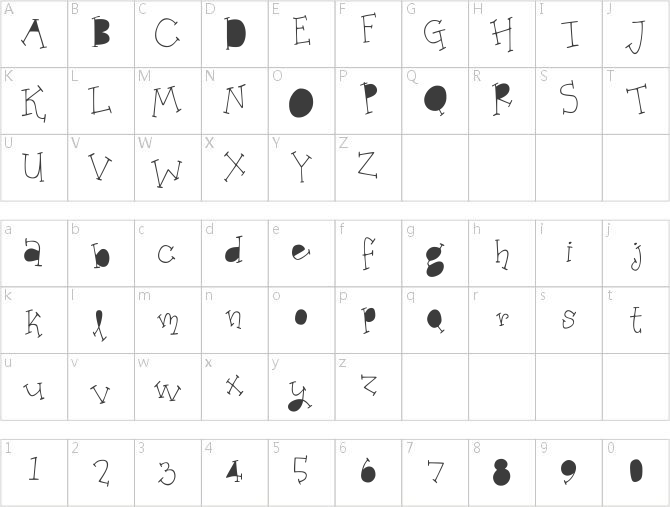
字體名稱: Organic
Organic-Fridays-solid-alternates
Organic-Fridays-solid-alternates字體字庫是一款讓人賞心悅目、百看不厭的英文字體,適合各類廣告和產品包裝設計應用,字體大小0.09MB,格式為ttf字體,上傳用戶是青檸檬,作者/版權方為未知